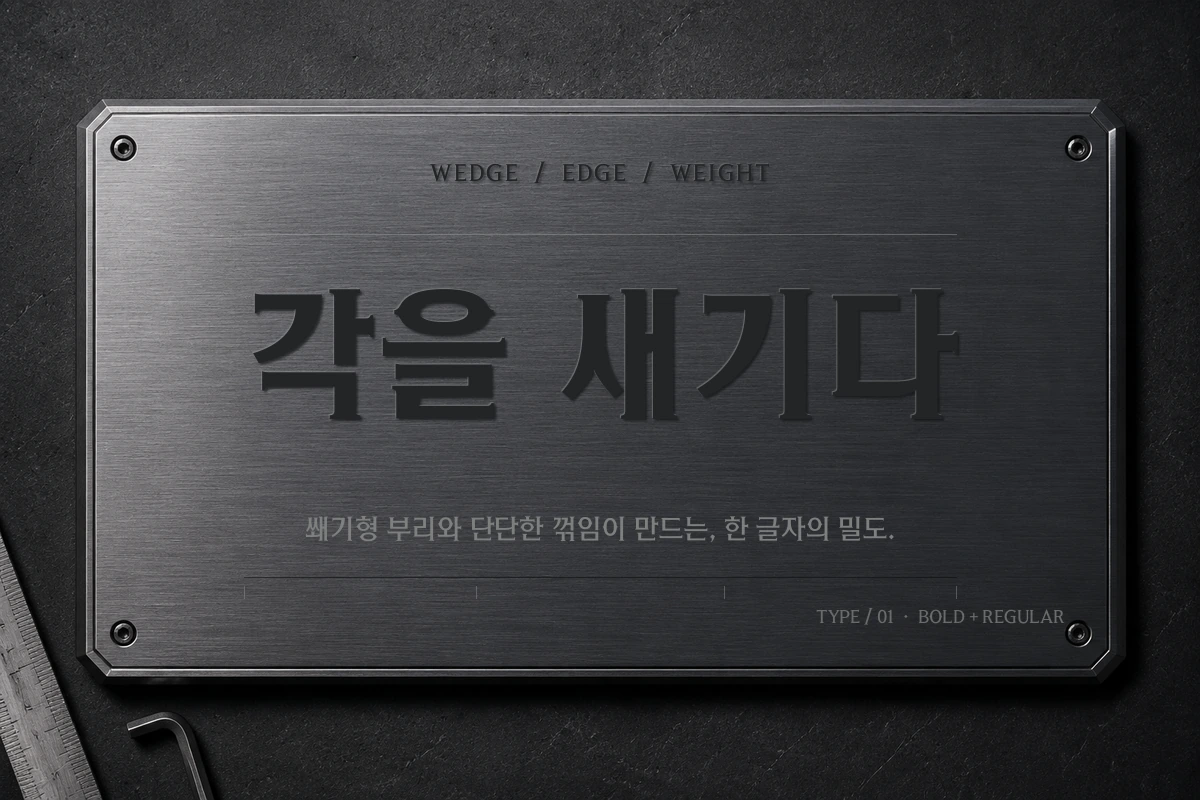
워헤이븐 무료폰트
워헤이븐 — 넥슨에서 배포하는 무료 폰트입니다. 고딕 구조에 쐐기 모양 세리프를 붙이고 꺾이는 지점을 각지게 처리한, 칼날처럼 단단한 서체
넥슨이 중세 전장을 배경으로 한 대전 액션 게임 워헤이븐에 맞춰 한글날 기념으로 배포한 서체입니다. 새로운 전장의 날이 서다라는 문구와 함께 공개됐습니다.
형태에 게임의 분위기가 담겨 있습니다. 고딕 구조에 쐐기 모양 세리프를 붙이고 획이 꺾이는 지점을 각지게 처리해, 칼날처럼 단단하고 직선적인 인상을 냅니다.